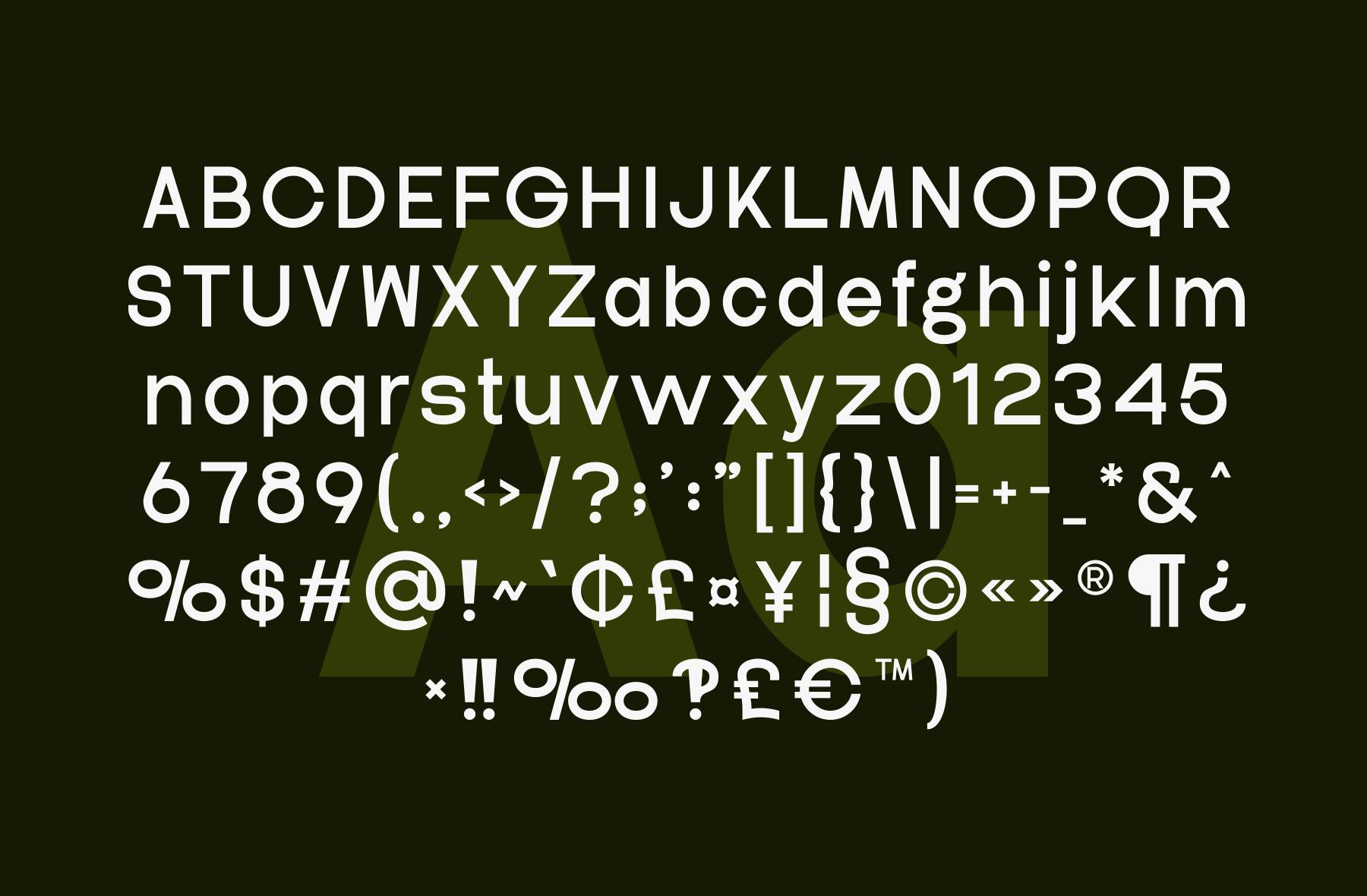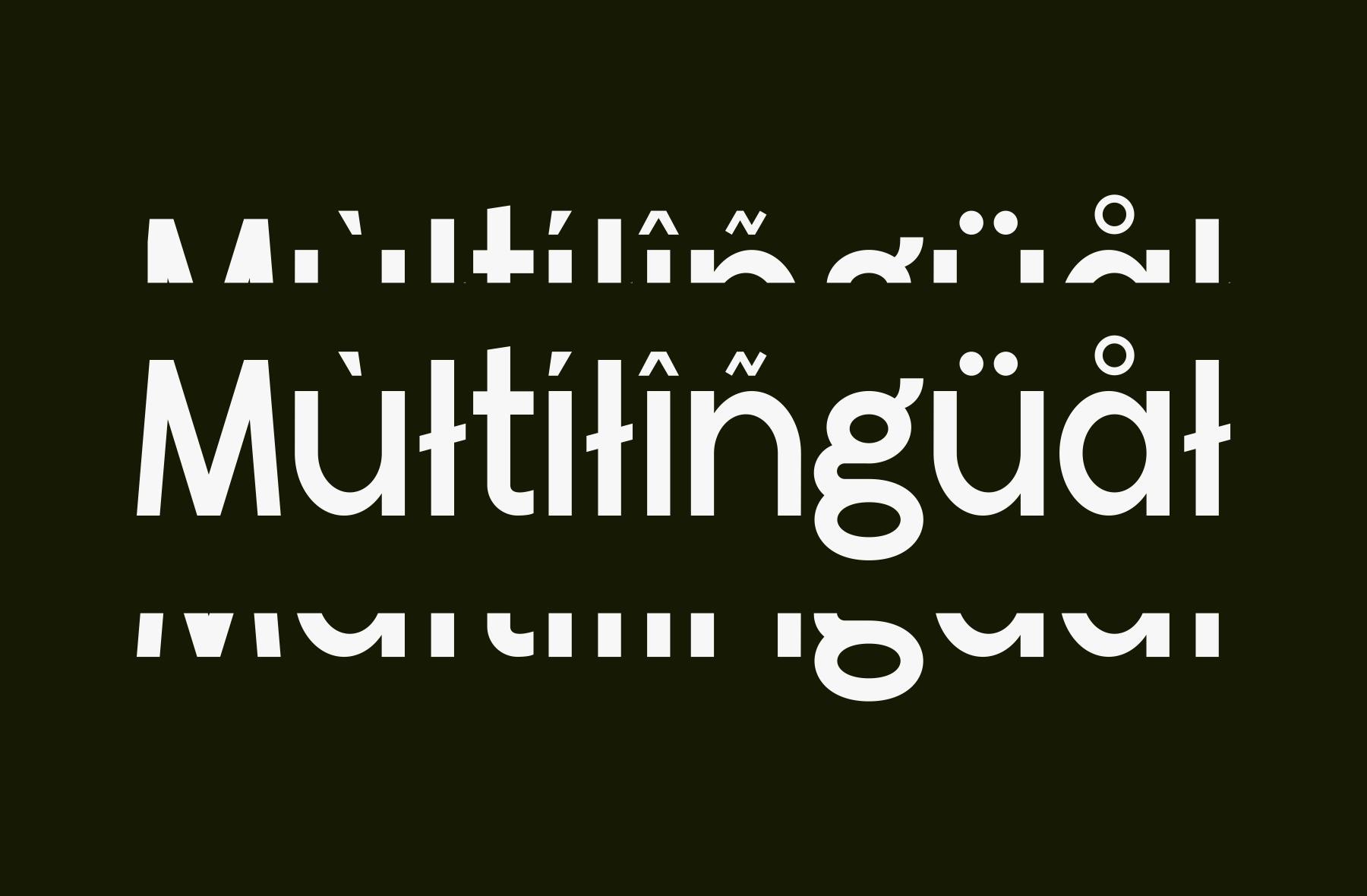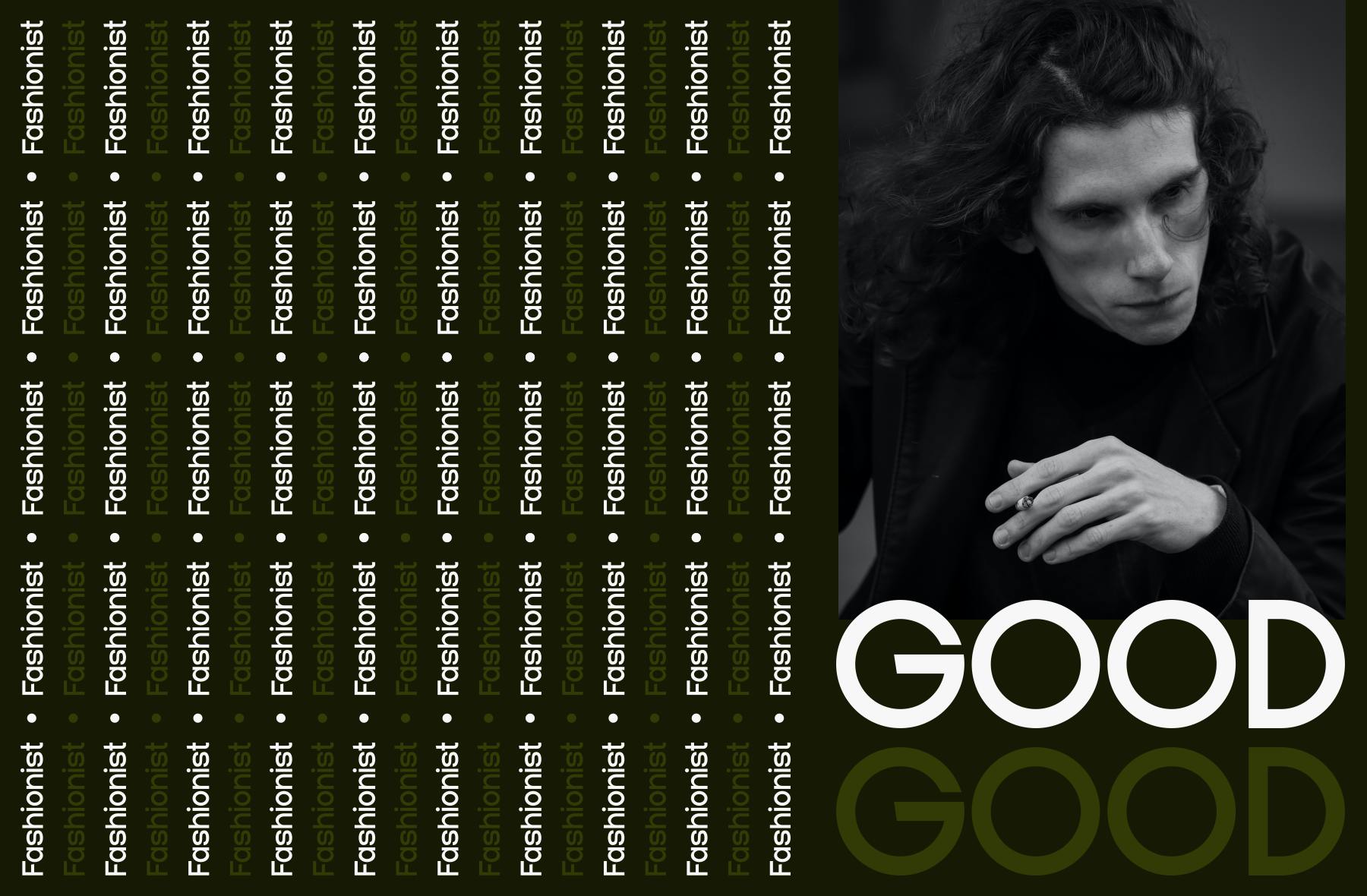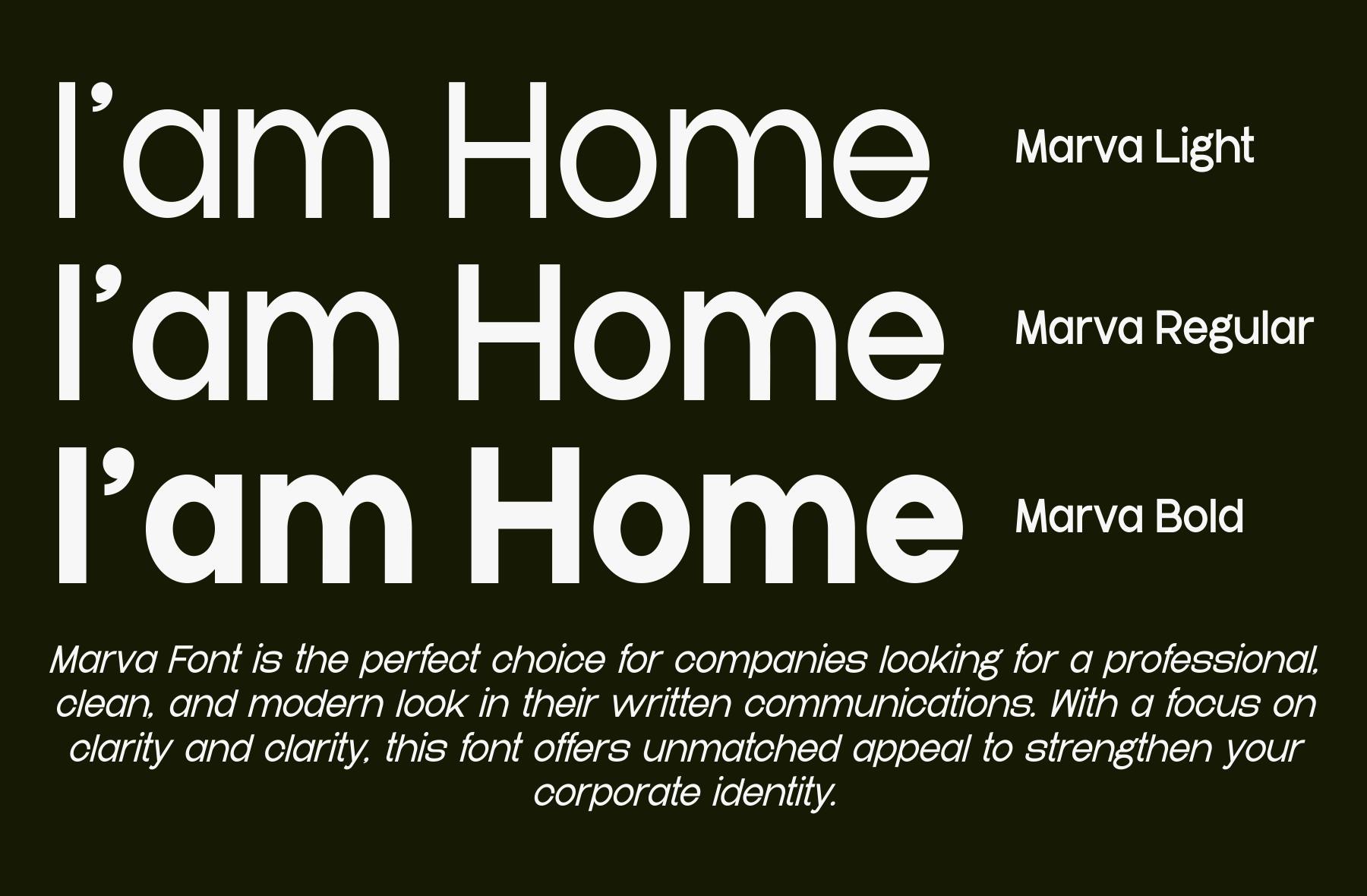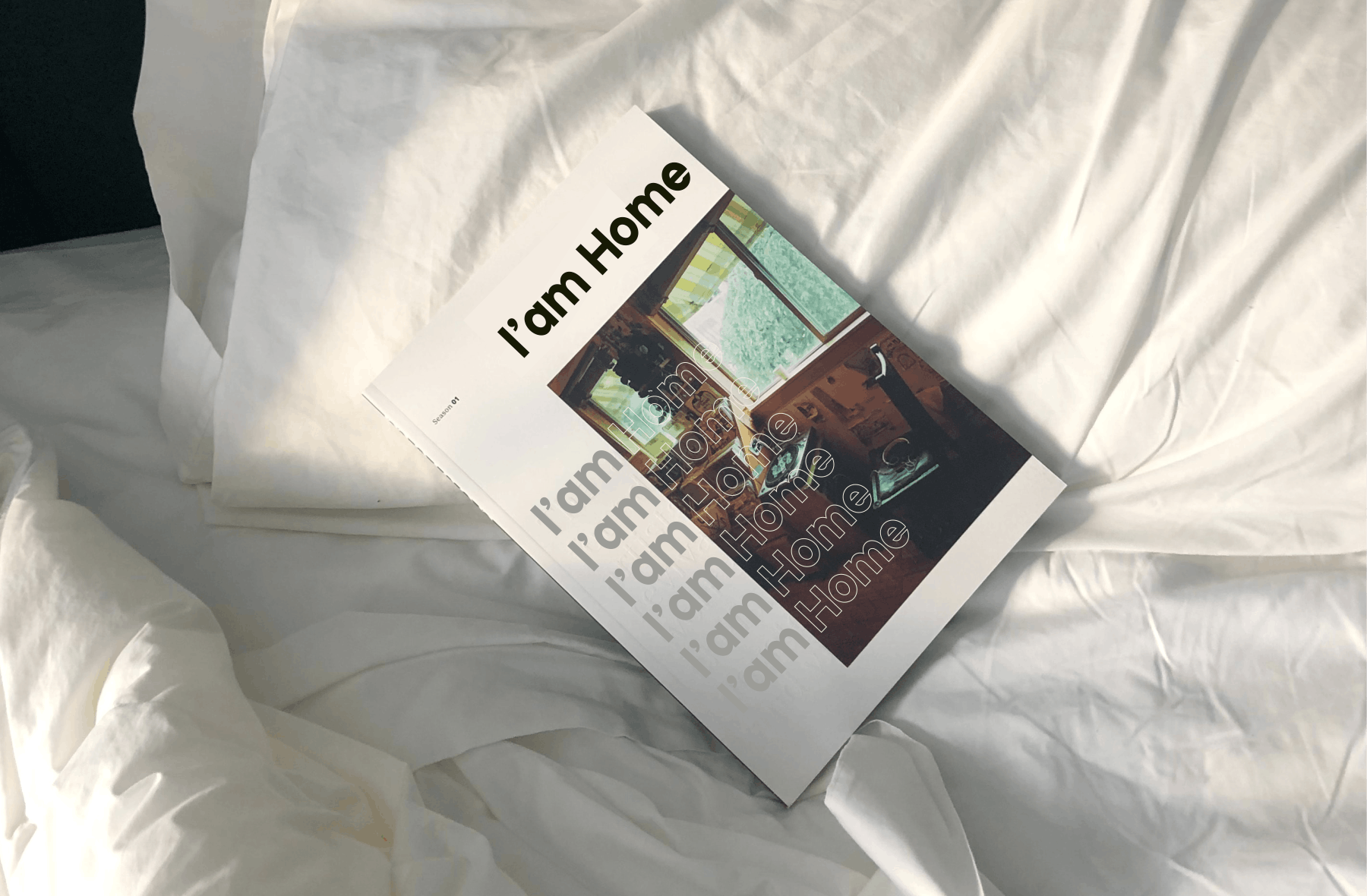
Marva A Modern Sans Family Font
معرفی محصول جدید ما فونت Marva - یک فونت مدرن و sans serif که برای هر پروژه برندینگ مانند لوگو، طراحی قالب، محصولات و بسیاری موارد دیگر مناسب است. این فونت در انواع مختلف زمینه‌ها برجسته و چشم‌نواز است.
• حروف بزرگ
• حروف کوچک
• چند زبانه